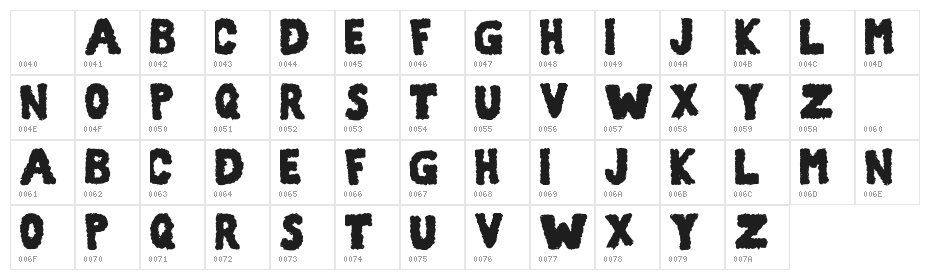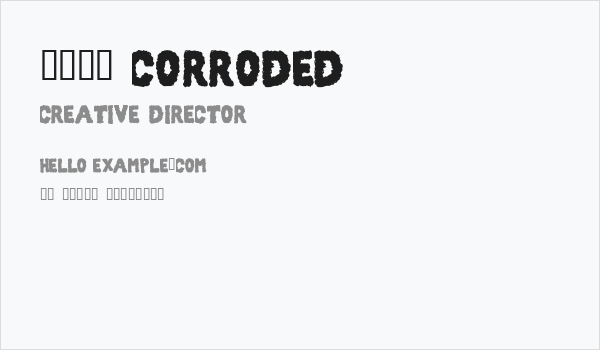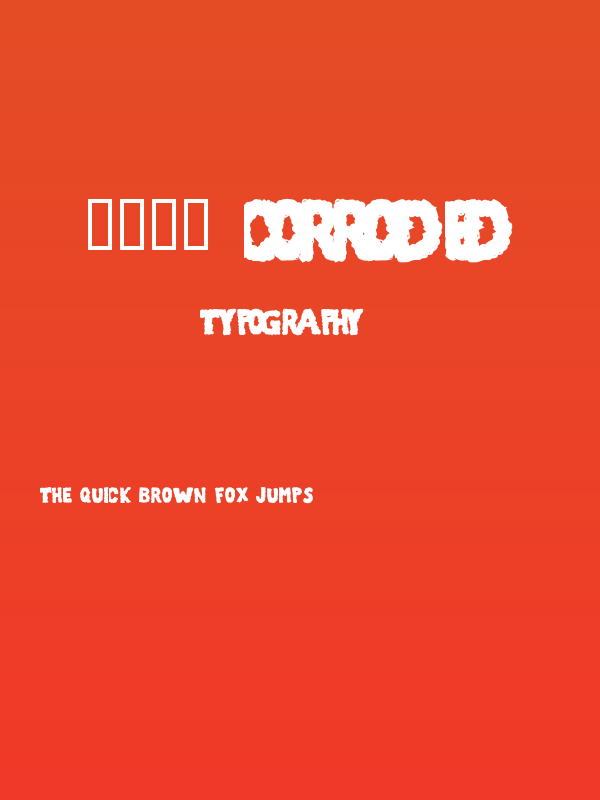
101! Corroded Font
✎ Distorted Eroded
| Progetti proposti | Ideal for projects requiring an industrial or grunge aesthetic, such as album covers, posters, or branding for edgy, alternative brands. |